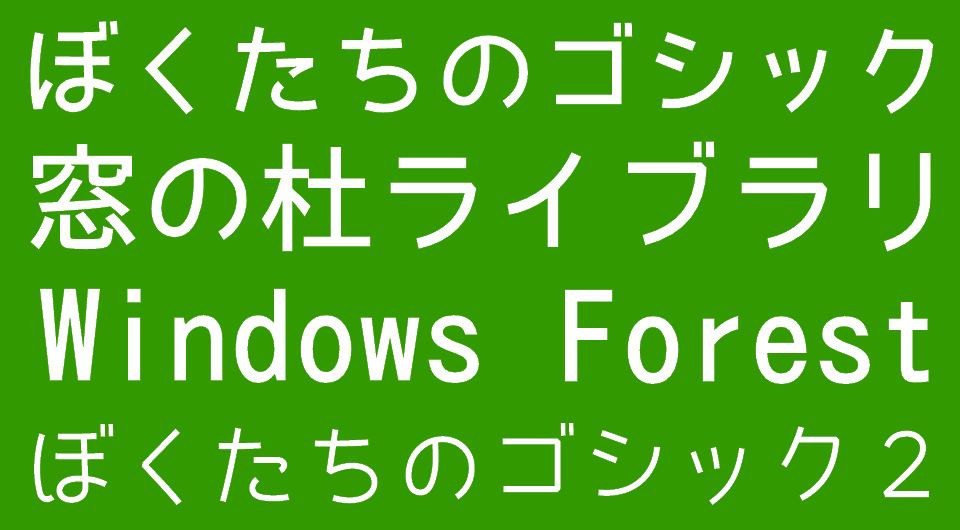
拙い仮名文字が元気な印象を与える日本語フォント「ぼくたちのゴシック」
「IPAゴシック」のクラシックな漢字に手書き感を加えた派生版
「ぼくたちのゴシック」は、「IPAゴシック」をもとに制作された派生フォント。作者は明確に言及していないものの、ひらがなとカタカナがオリジナルデザインと推測され、「IPAゴシック」はJIS第四水準までの漢字を網羅する。
オリジナルの仮名文字はかわいらしさよりも拙さが少し勝るようなデザイン。クラシックな「IPAゴシック」に手書き感が加わることで、明るく元気な印象を受け、ひらがなをとくに多用したくなる。
また、「源ノ角ゴシック」をもとに制作された姉妹フォント「ぼくたちのゴシック2」も公開されており、仮名文字の基本的なデザインはそのままに、丸みが強調されている。「ぼくたちのゴシック」を男の子とすれば、「ぼくたちのゴシック2」は女の子といったところだろうか。